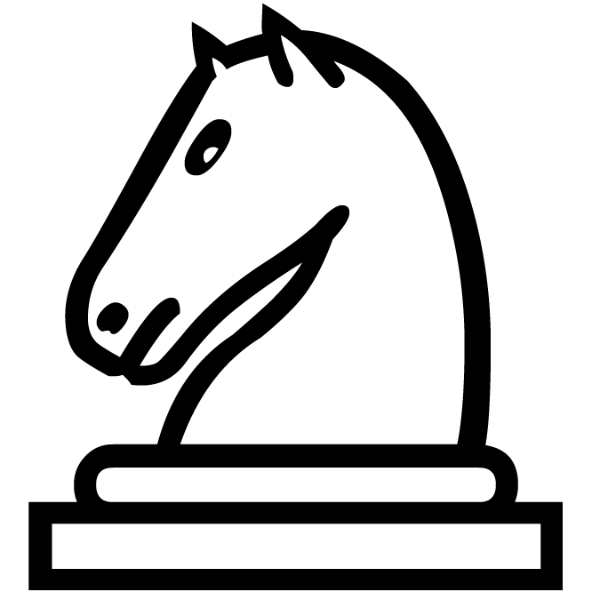
Fuente de Ajedrez Chess Lucena – Destacada por sus bases dobles y el diseño puntiagudo en todas las piezas, especialmente en el Rey, Chess Lucena es una fuente que combina elegancia y funcionalidad. Diseñada por Armando Hernandez Marroquin, esta tipografía freeware es ideal para proyectos ajedrecísticos, diagramas y diseño gráfico. Puedes descargarla, instalarla y comenzar a usarla fácilmente en tu ordenador. A continuación, encontrarás algunas imágenes de muestra y el enlace para la descarga.